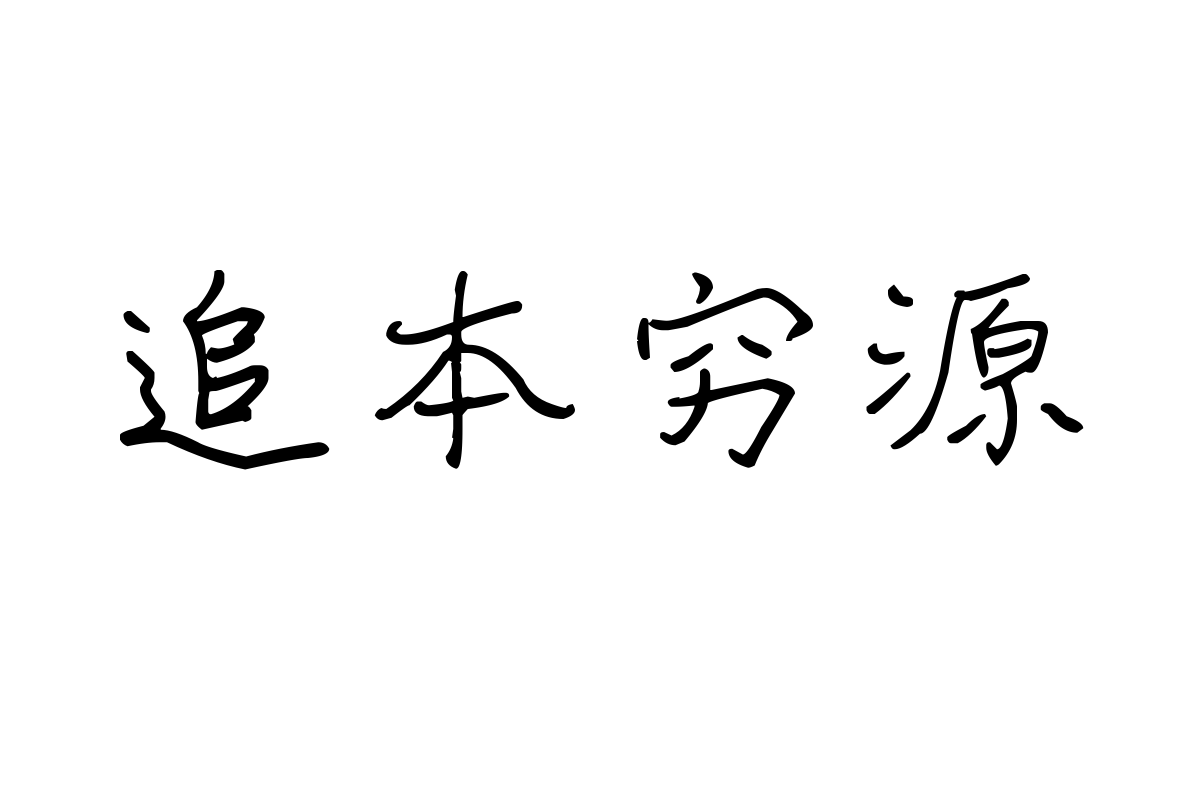
蝉羽钦魏字体是一套具有中国风格的书法字体,由设计师李振华创作。这套字体以传统的汉字为基础,结合了现代设计元素,创造出既具有传统韵味又不失现代感的字体。蝉羽钦魏字体的特点是字形圆润流畅,线条细腻有力,既有古典的美感,又不失现代的设计感。
蝉羽钦魏字体适用于各种印刷品、广告、包装、网站等场景,能够很好地传达出中国传统文化的魅力。同时,由于其独特的设计风格,也受到了许多设计师和艺术家的喜爱和追捧。